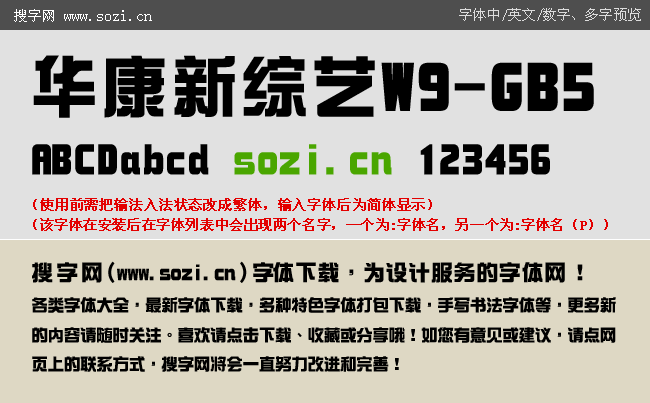
華康新綜藝體W9-GB5
搜字網(wǎng)提供一款華康新綜藝體W9-GB5下載。綜藝體是黑體的一種變體,也是藝術(shù)字的一種。特點(diǎn)是筆劃更粗,盡量將空間充滿(mǎn)。同時(shí)為了美觀,對(duì)拐彎處的處理較為圓潤(rùn)。適用于廣告、報(bào)刊等的標(biāo)題及海報(bào)展板等設(shè)計(jì)場(chǎng)合使用。